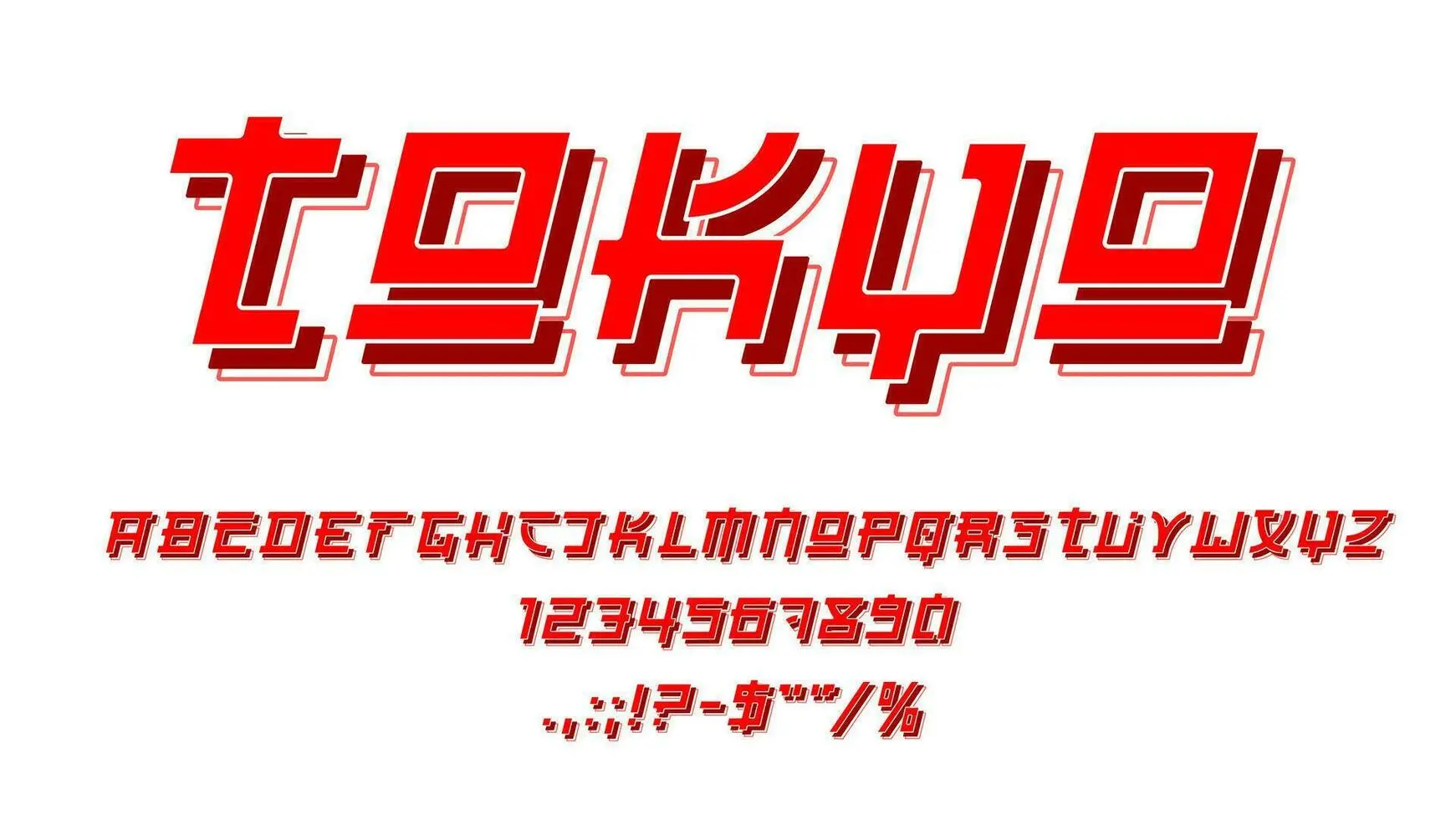
El entorno del diseño gráfico está lleno de estilos y tendencias, y una de las que ha ganado mucha popularidad en los últimos años es la tipografía anime. Influenciada por el vibrante y expresivo arte del anime y el manga, esta estética única ofrece una amplia gama de posibilidades creativas para diseñadores de todo tipo.
Pero, ¿qué define exactamente una fuente anime ? ¿Qué la diferencia de otros estilos tipográficos? En este artículo, exploraremos a fondo el entorno de las fuentes de anime, analizando sus características, su historia, y cómo se pueden utilizar eficazmente en diversos proyectos de diseño.
Características de las Fuentes Anime
Las fuentes de estilo anime se caracterizan por una serie de rasgos distintivos que las hacen fácilmente reconocibles. A menudo, presentan una combinación única de elementos que evocan la estética del anime y el manga:
- Líneas Dinámicas y Energéticas: Las curvas pronunciadas, los ángulos agudos y las líneas irregulares son comunes, creando una sensación de movimiento y vitalidad.
- Variedad de Grosores: El uso de grosores variables en las letras, con trazos finos y gruesos contrastantes, agrega profundidad y textura al texto.
- Influencia de la Caligrafía Japonesa: Algunas fuentes incorporan elementos de la caligrafía japonesa, como trazos estilizados y una sensación de fluidez.
- Elementos Decorativos: Detalles como serifs estilizados, adornos y efectos especiales pueden añadir personalidad y encanto a la fuente.
- Paleta de Colores Vibrantes: Aunque la fuente en sí misma es monocromática, su uso se suele acompañar de paletas de color vibrantes que potencian la estética anime.
- Efectos 3D y Sombras: Algunos diseños incorporan efectos 3D o sombras para dar volumen y profundidad a las letras.
Historia y Evolución de las Fuentes Anime
La evolución de las fuentes anime está intrínsecamente ligada a la historia del anime y el manga. Si bien no existe un punto de origen específico, se puede observar una progresión natural desde las fuentes más tradicionales hacia estilos más estilizados y expresivos. La creciente popularidad del anime a nivel mundial ha impulsado la creación de una gran variedad de fuentes de inspiración anime, adaptadas a diferentes necesidades y preferencias de diseño.
Inicialmente, las fuentes utilizadas en la industria del anime eran más funcionales y sencillas. Con el tiempo, la demanda de estilos más distintivos y expresivos llevó al desarrollo de tipografías anime más elaboradas, que reflejan la complejidad y la riqueza visual del propio anime.
Tipos de Fuentes Anime
Existe una gran variedad de fuentes de estilo anime, cada una con sus propias características únicas. Podemos clasificarlas en diferentes categorías según su estilo:
- Fuentes Kawaii: Caracterizadas por su ternura y dulzura, con formas redondeadas y detalles encantadores.
- Fuentes Grungy: Presentan un estilo más áspero y texturizado, con elementos que evocan la estética del graffiti o el cómic.
- Fuentes Futurísticas: Inspirándose en la ciencia ficción, suelen incorporar elementos geométricos y tecnológicos.
- Fuentes Retro: Recuerdan a los estilos tipográficos de los años 80 y 90, a menudo con un toque nostálgico.
- Fuentes Minimalistas: Aunque mantienen la esencia del estilo anime, se enfocan en la simplicidad y la limpieza.
Usos de las Fuentes Anime en el Diseño
La versatilidad de las fuentes anime las hace ideales para una amplia gama de aplicaciones de diseño. Algunos ejemplos incluyen:
- Diseño de Logos y Marcas: Una fuente anime bien elegida puede crear un logo memorable y distintivo para una empresa o producto.
- Diseño de Pósters y Folletos: Ideales para captar la atención y transmitir la energía y la emoción del anime.
- Diseño Web: Pueden utilizarse para crear encabezados, títulos y otros elementos visuales en páginas web.
- Diseño de Videojuegos: Las fuentes anime pueden añadir un toque distintivo a los juegos, especialmente en aquellos con una estética anime.
- Diseño de Packaging: Para crear un packaging atractivo y llamativo para productos relacionados con el anime o el manga.
Tabla Comparativa de Fuentes Anime
| Nombre de la Fuente | Estilo | Características | Usos Recomendados |
|---|---|---|---|
| Fuente A | Kawaii | Redondeada, suave | Logos infantiles, packaging de dulces |
| Fuente B | Grungy | Texturizada, áspera | Pósters de eventos musicales, diseño de videojuegos |
| Fuente C | Futurística | Geométrica, moderna | Diseño web, interfaces de usuario |
| Fuente D | Retro | Nostálgica, pixelada | Diseño de videojuegos retro, posters vintage |
| Fuente E | Minimalista | Limpia, elegante | Logos corporativos, diseño editorial |
Consejos para Usar Fuentes Anime
Para utilizar eficazmente las fuentes anime en tus proyectos, ten en cuenta los siguientes consejos:
- Considera el Contexto: Asegúrate de que la fuente se adapte al mensaje y al público objetivo.